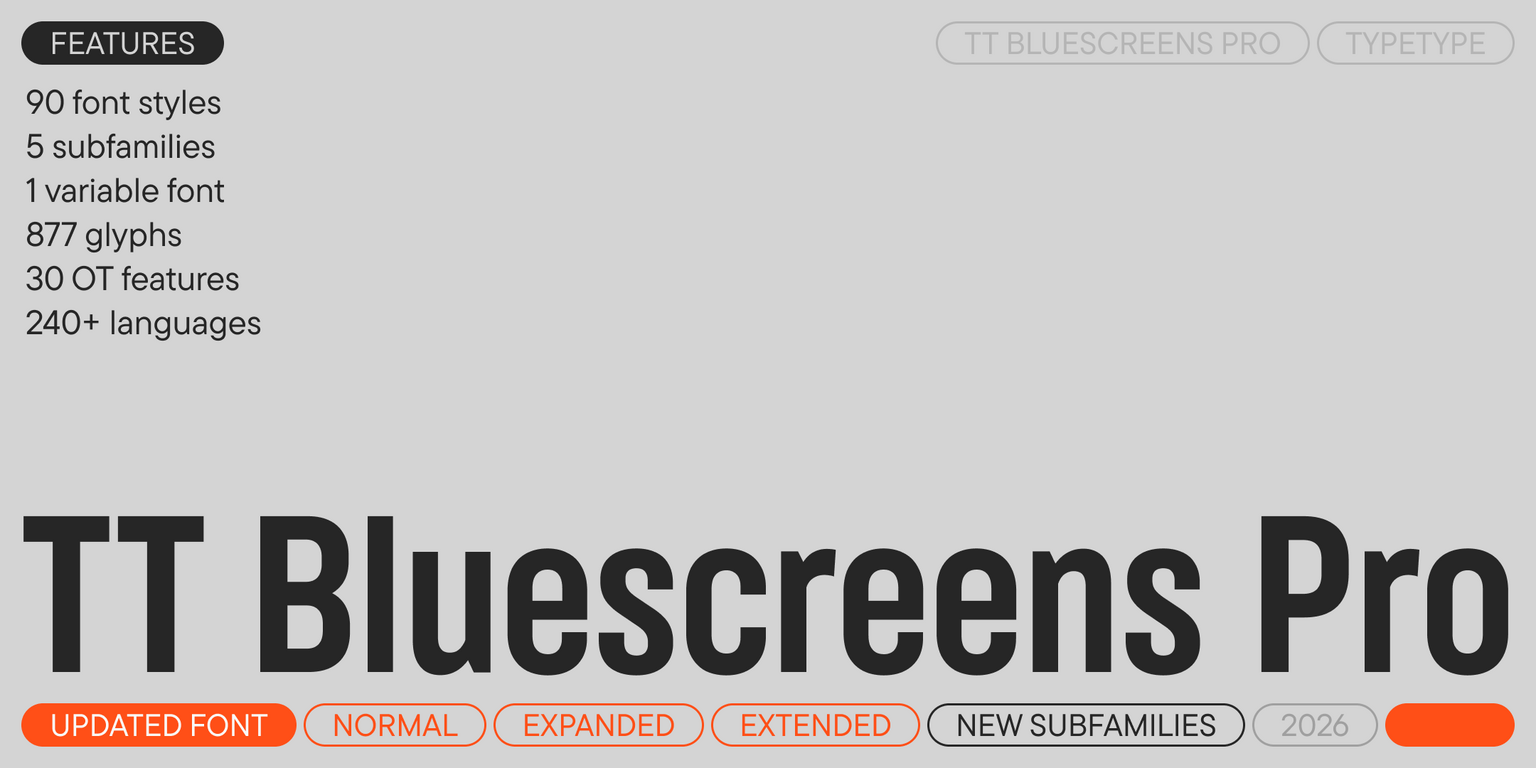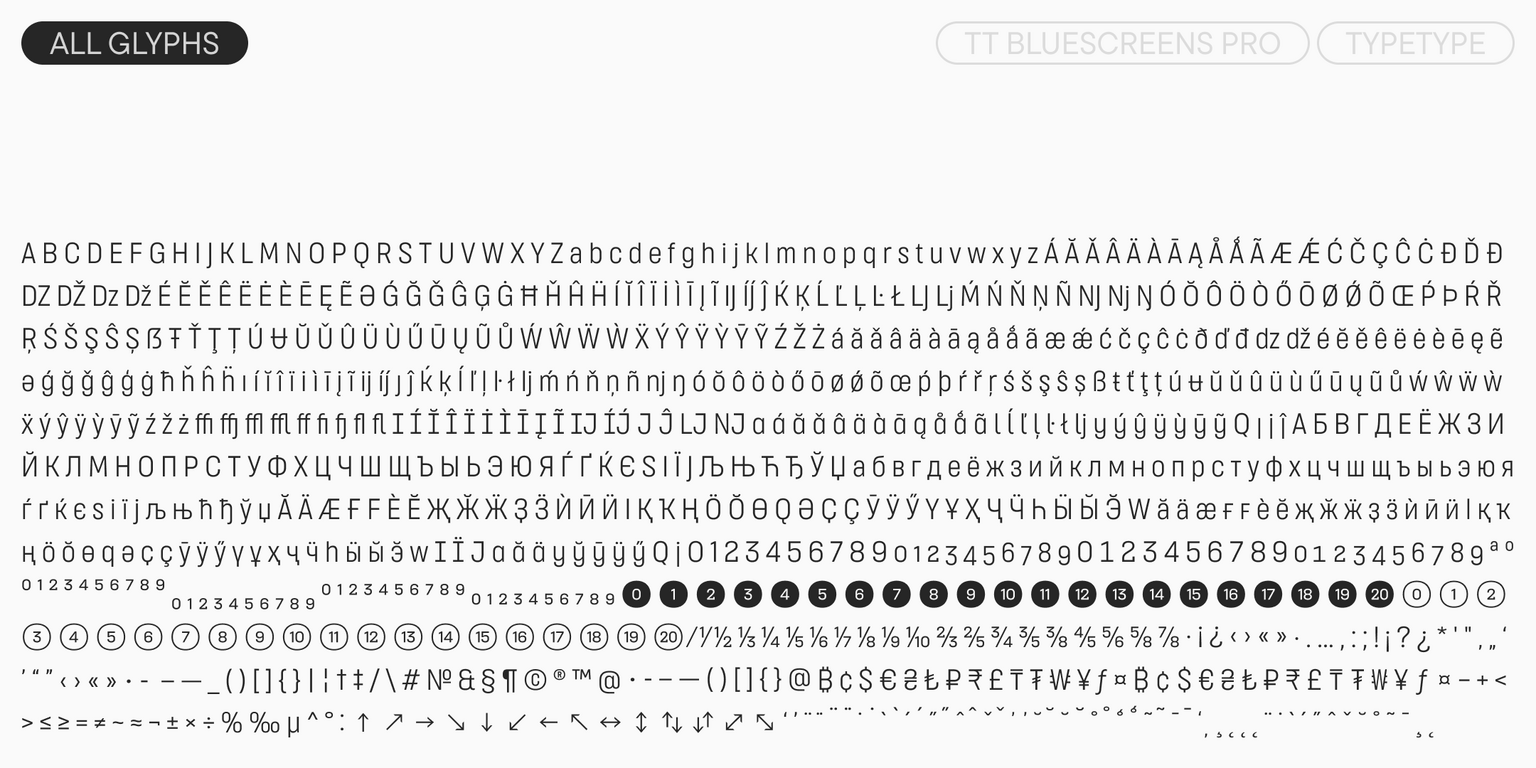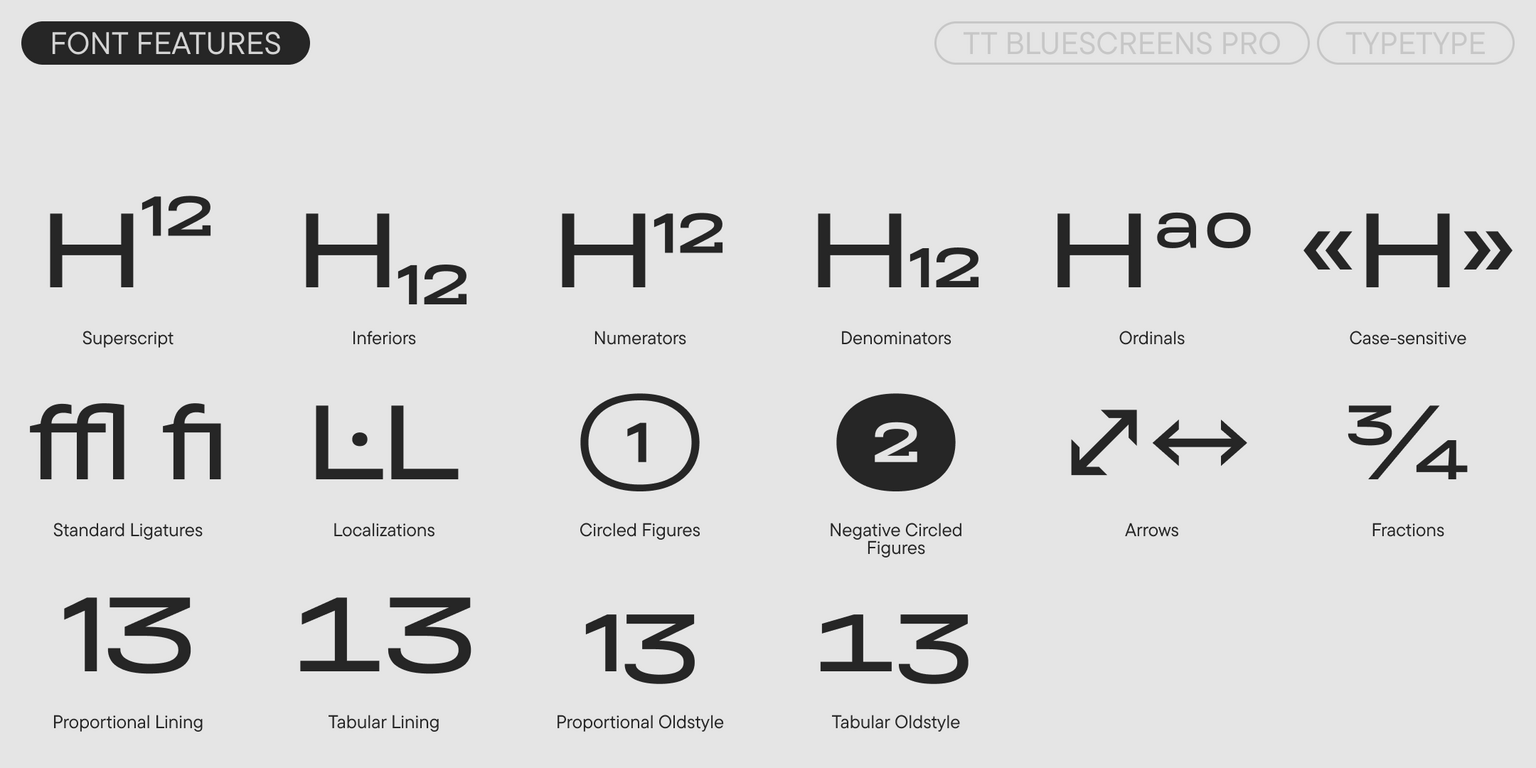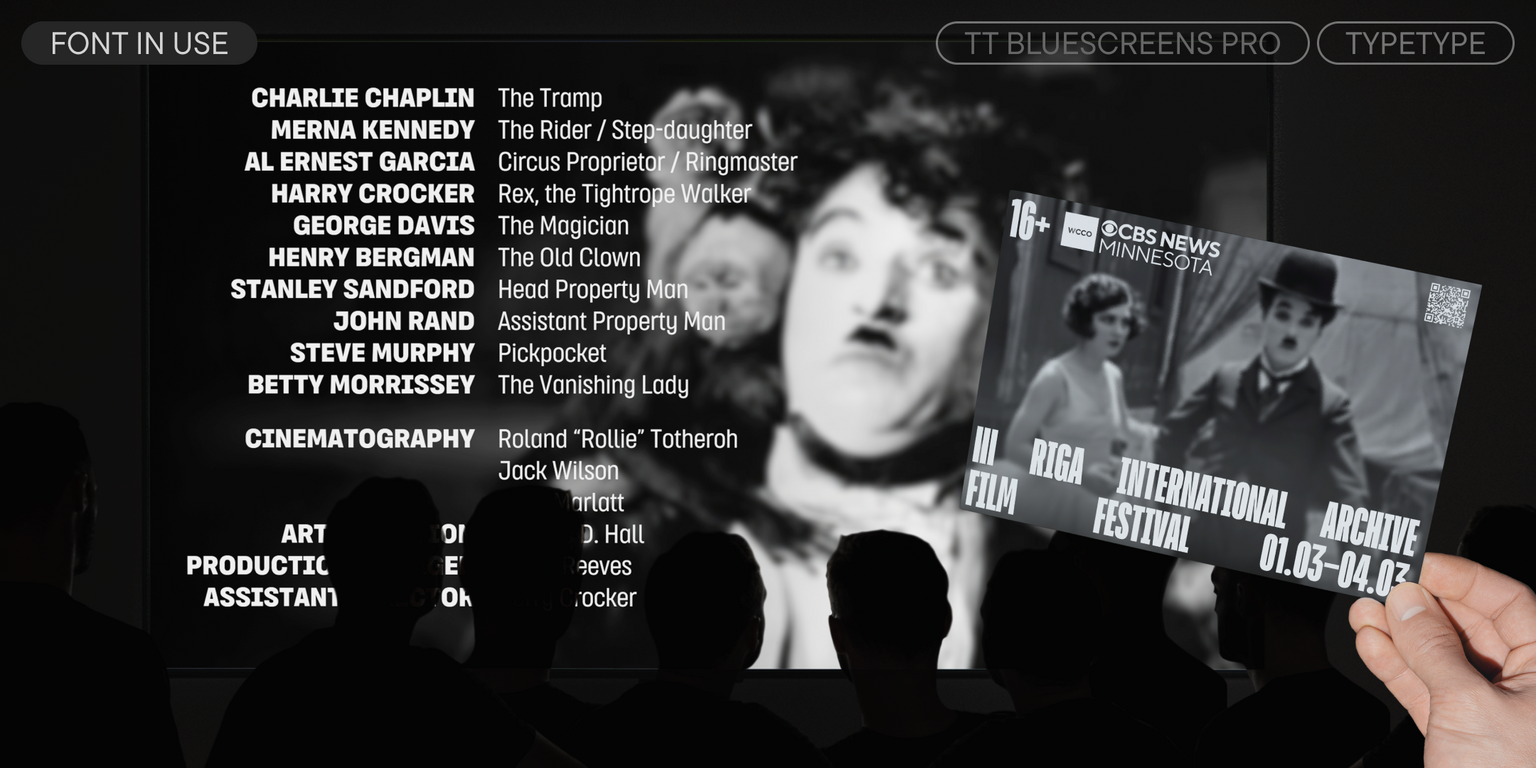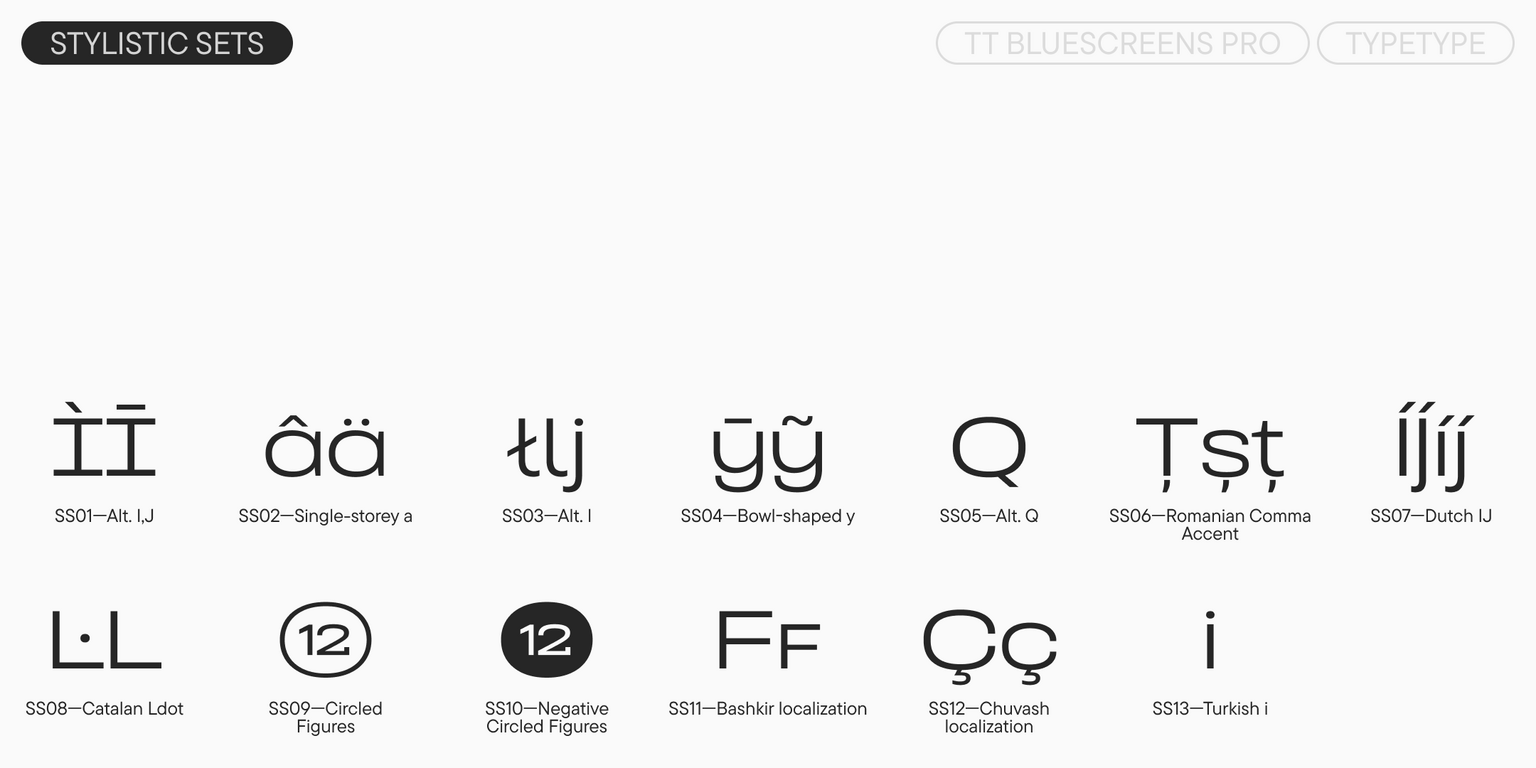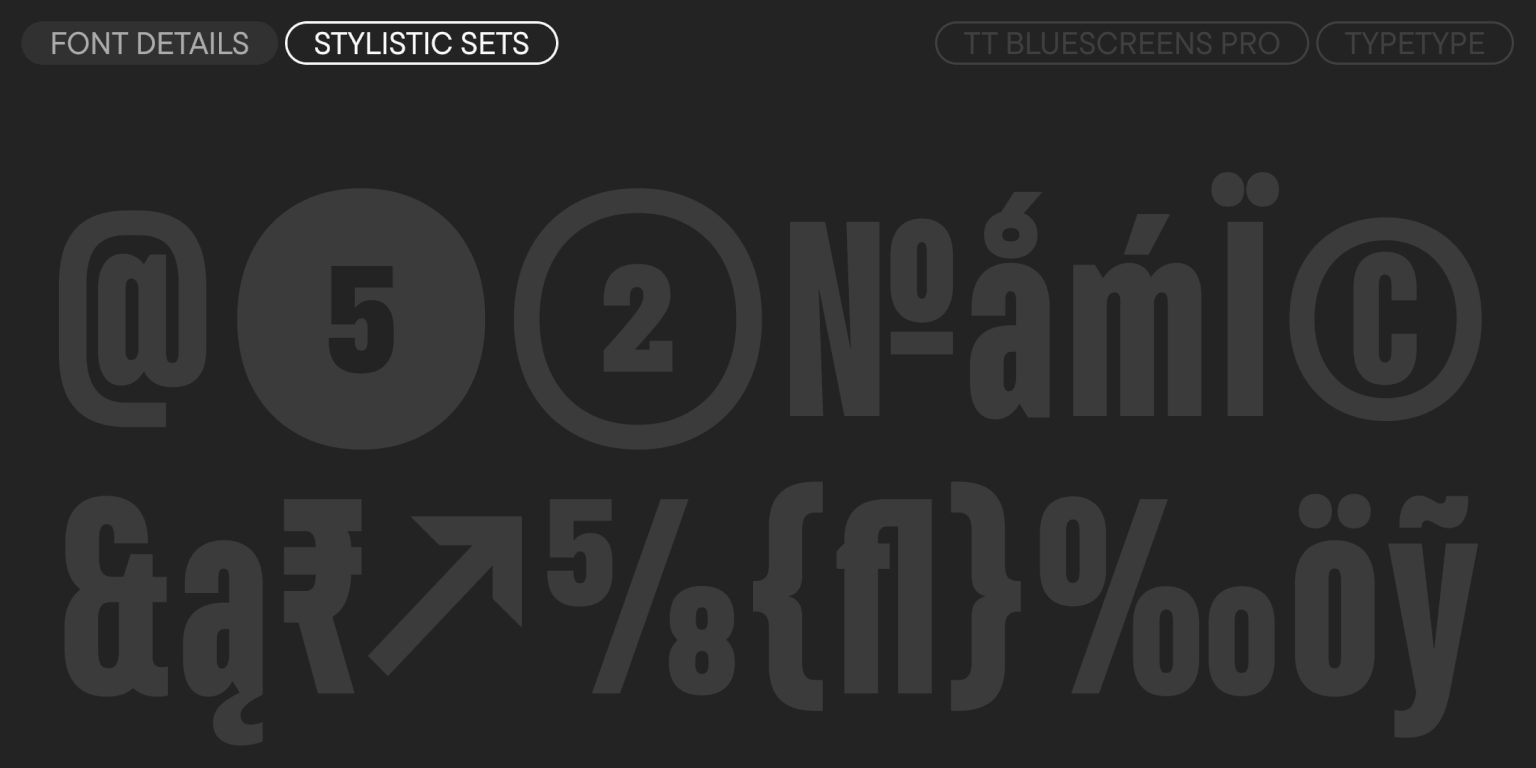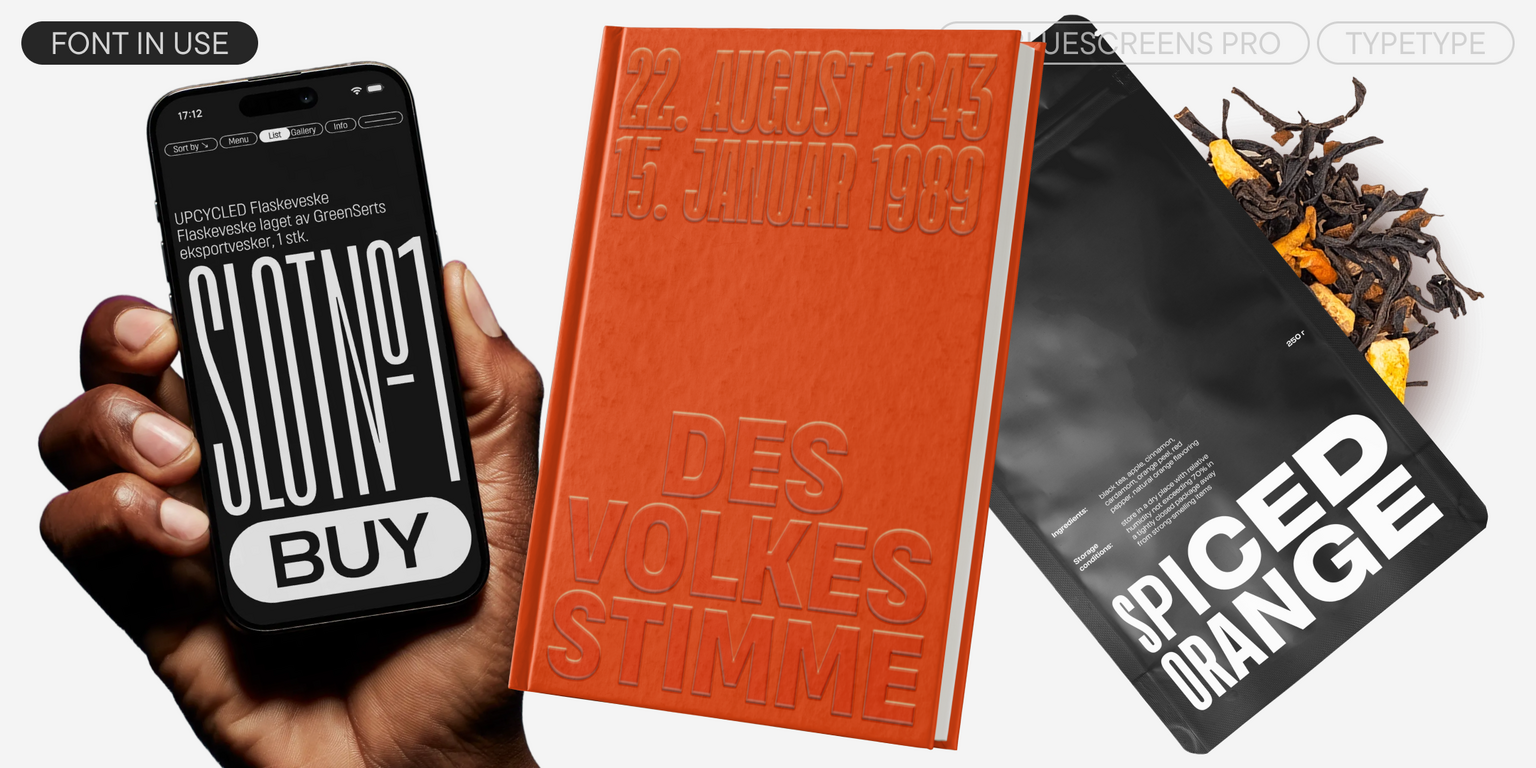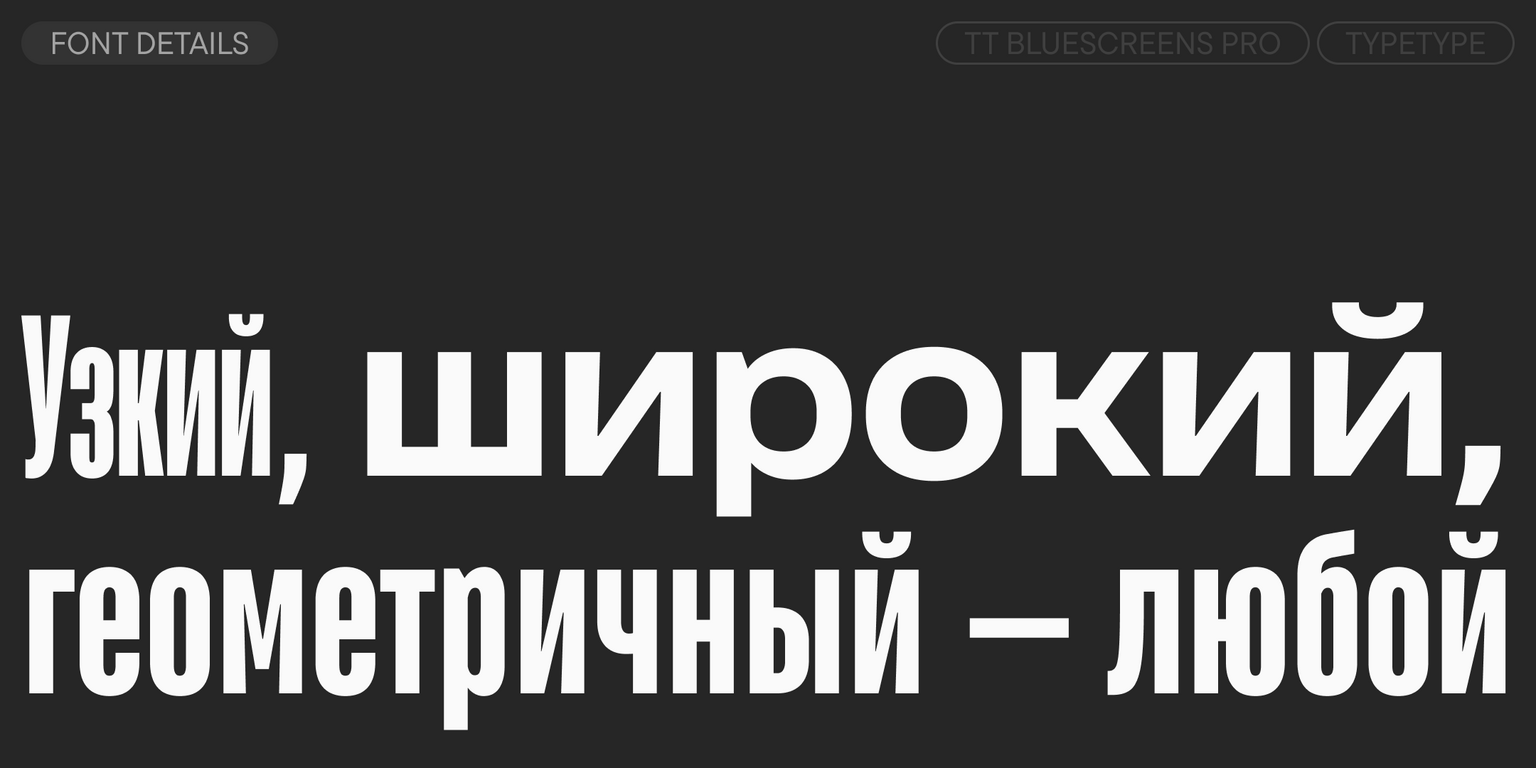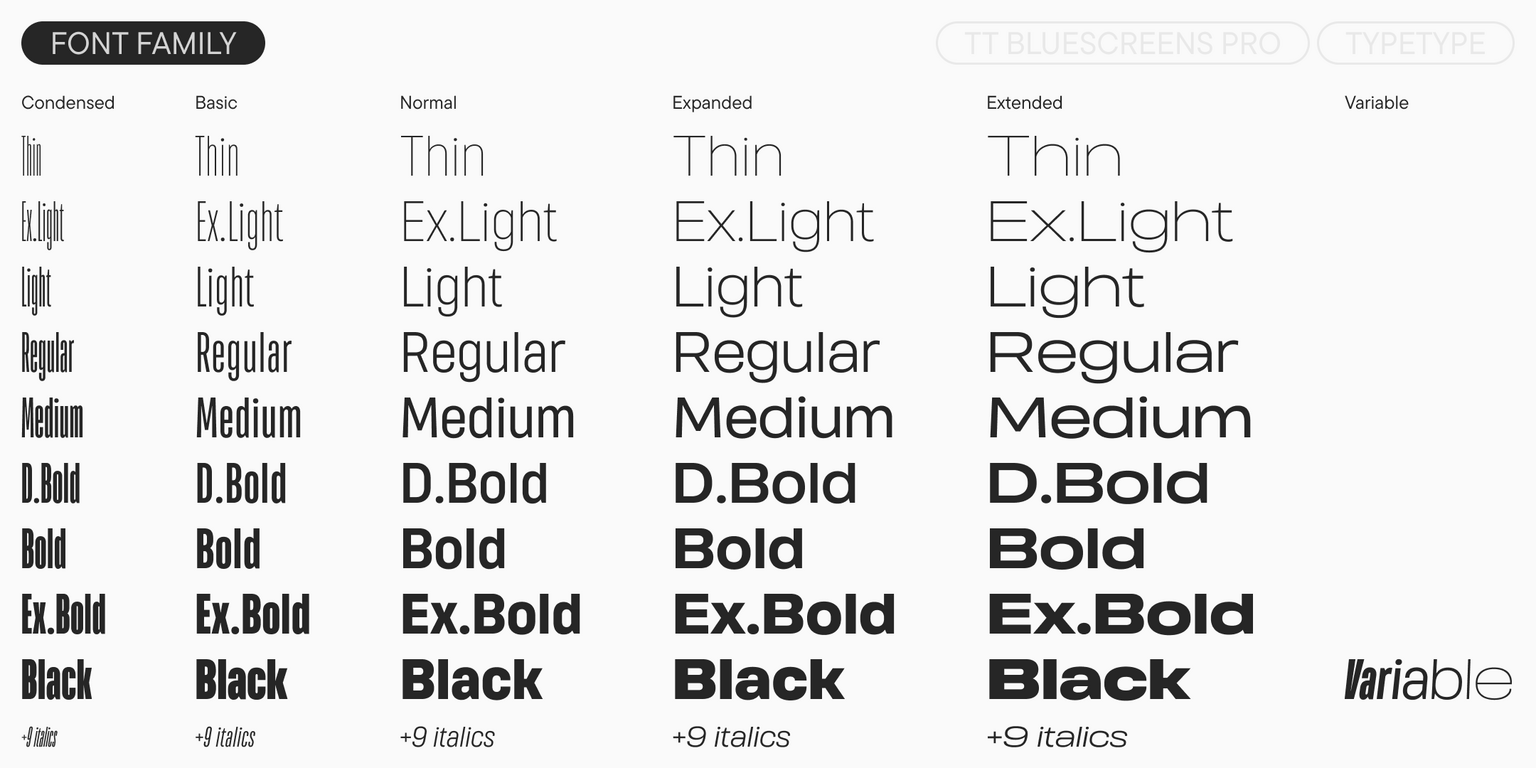
TT Bluescreens Pro
TT Bluescreens Pro — ТТ Блюскринс Про
Произносится «ТТ Блюскринс Про». «Bluescreens» — производное слово от двух слов blue (с английского «синий») и screen (с английского «экран»). «Pro» произносится как «про», и является разговорным сокращением слова «профессиональный». Буквы «TT» являются аббревиатурой названия компании.
TT Bluescreens Pro — дисплейный неогротеск с узкими пропорциями. Это шрифт со спокойным, но в то же время запоминающимся характером.
TT Bluescreens Pro
TT Bluescreens Pro — модульный гротеск с самобытным характером
TT Bluescreens Pro
В 2015 году мы создали это шрифтовое семейство специально для киноафиш и титров. Изначально это был узкий модульный гротеск, но со временем TT Bluescreens полюбился нам за свой самобытный, по-настоящему акцидентный характер. В 2023 году мы выпустили третью версию шрифта, дополнив её ещё более узким подсемейством, расширенной кириллицей, новым кернингом и хинтингом. Однако на этом мы не остановились. У нас появилась идея, которая сперва показалась безумной, но оказалась вполне рациональной: что, если сделать TT Bluescreens настолько широким, насколько это возможно? Сначала мы сами смеялись над этой затеей, но всё же взялись за эксперимент — и результат нас искренне удивил. В начале 2026 года мы представляем TT Bluescreens Pro — четвёртую версию нашей легендарной гарнитуры. В неё вошли три новых подсемейства: Normal, Expanded и Extended. Такой широкий диапазон ширины даёт практически неограниченные возможности для дизайна. Мы также обновили вариативный шрифт, который теперь объединяет все пять подсемейств в единую вариативную вселенную.